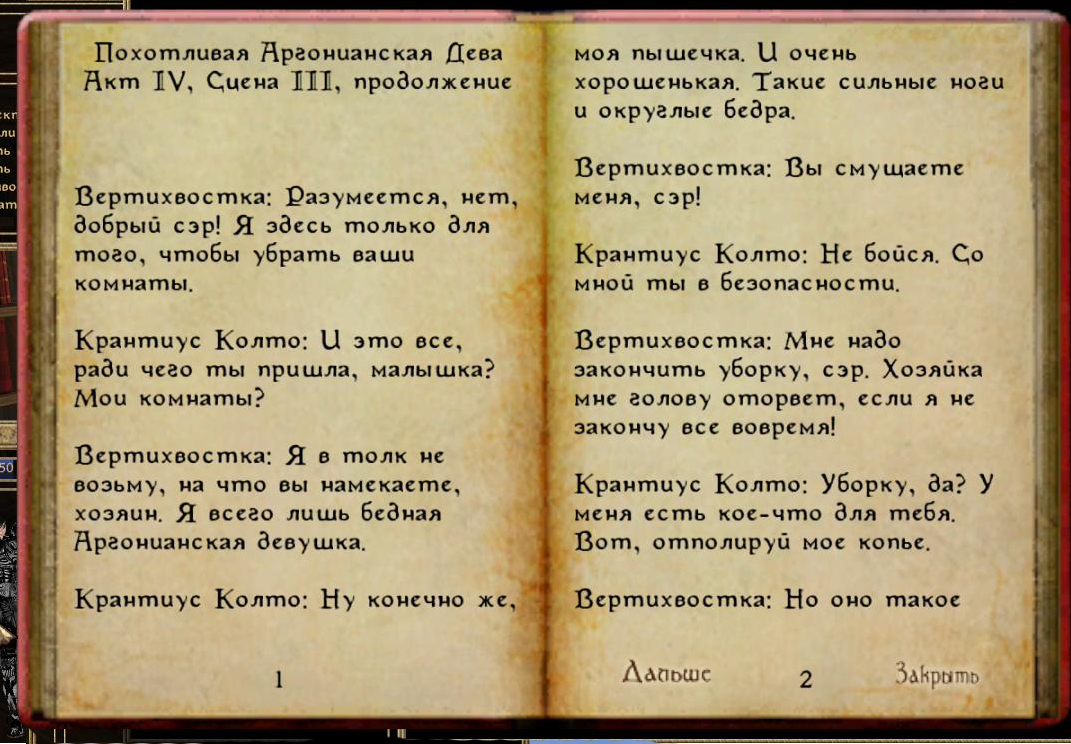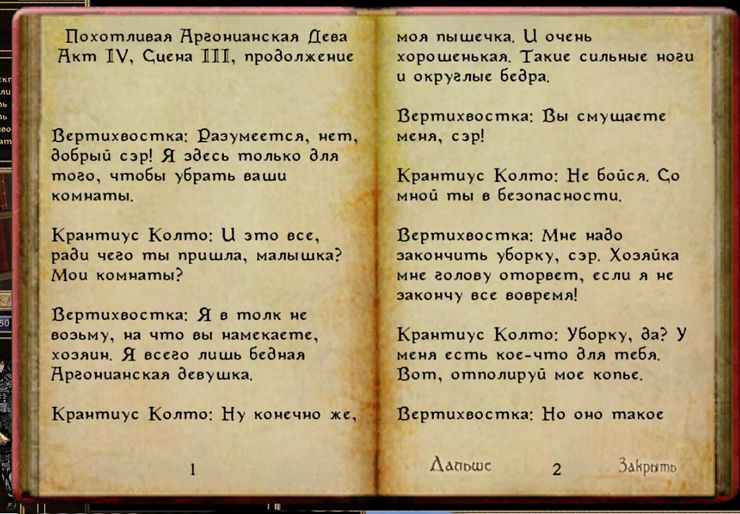
Это улучшенная версия шрифта Magic Cards, чаще всего используемого в меню, диалогах и журнале. Реплейсер поднимает четкость без изменения размера шрифта.
Шрифт сделан на основе оригинальной версии, специфичной для Морровинда, шрифт стал темнее.
Хороший шрифт,читабельность значительно повышается. Я лично после установки данного шрифта
ещё меняю в текстовом файле morrowind.ini в папке с игрой значение color normal=255,255,255. В итоге шрифт диалогов становится белым и читабельность повышается в разы.
Диалоги то норм, а вот дневник все огромное и не влазит на страницы!
Классная вещь. Шрифт в журнале особенно мыльный был раньше.
Превосходно. Но как сделать, чтобы запись была на одной странице?.